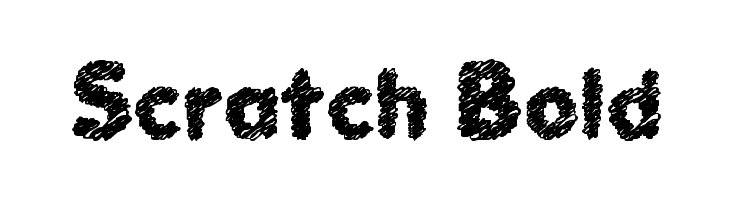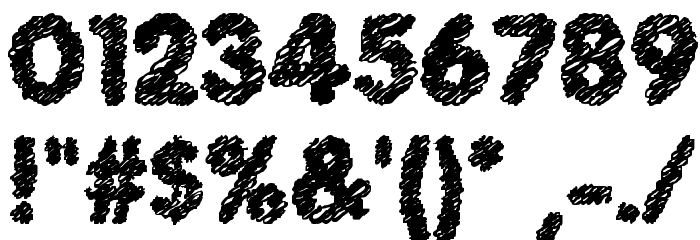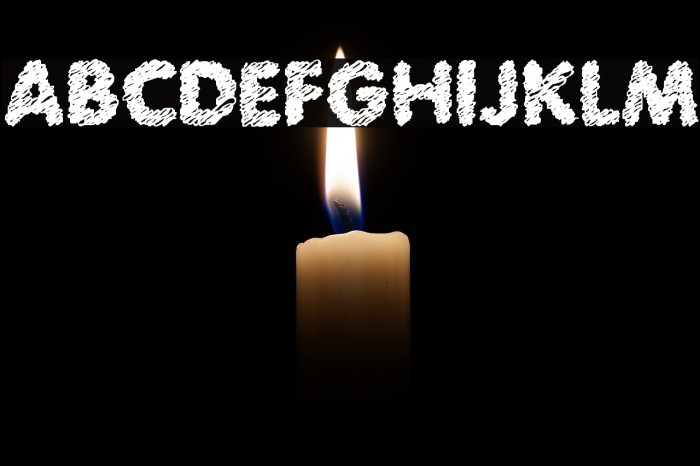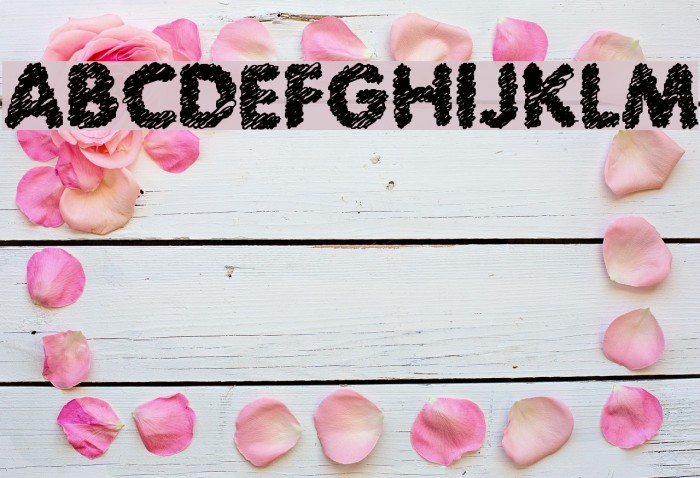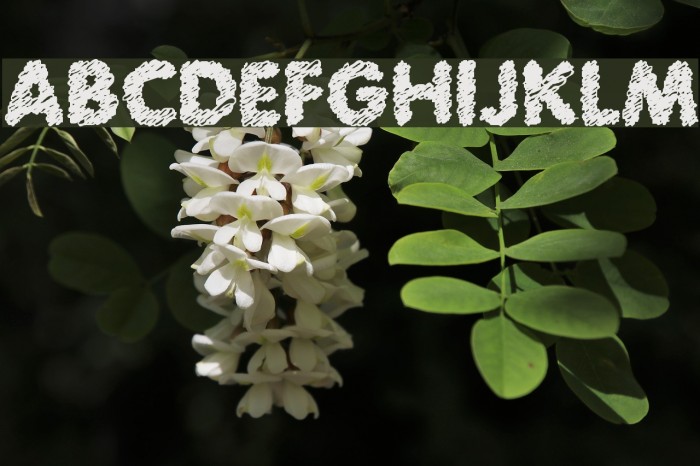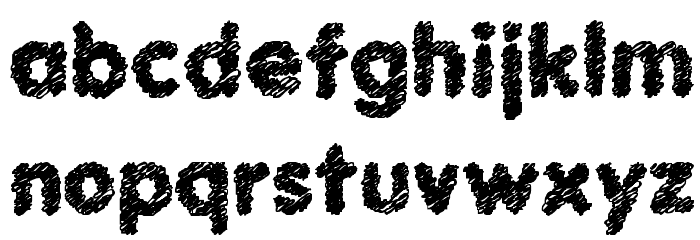
Scratch Bold Font
| Proiecte propuse | Ideal for creative projects such as posters, album covers, and artistic branding. It can also be used in digital art, social media graphics, and any design requiring a bold, expressive typeface. |